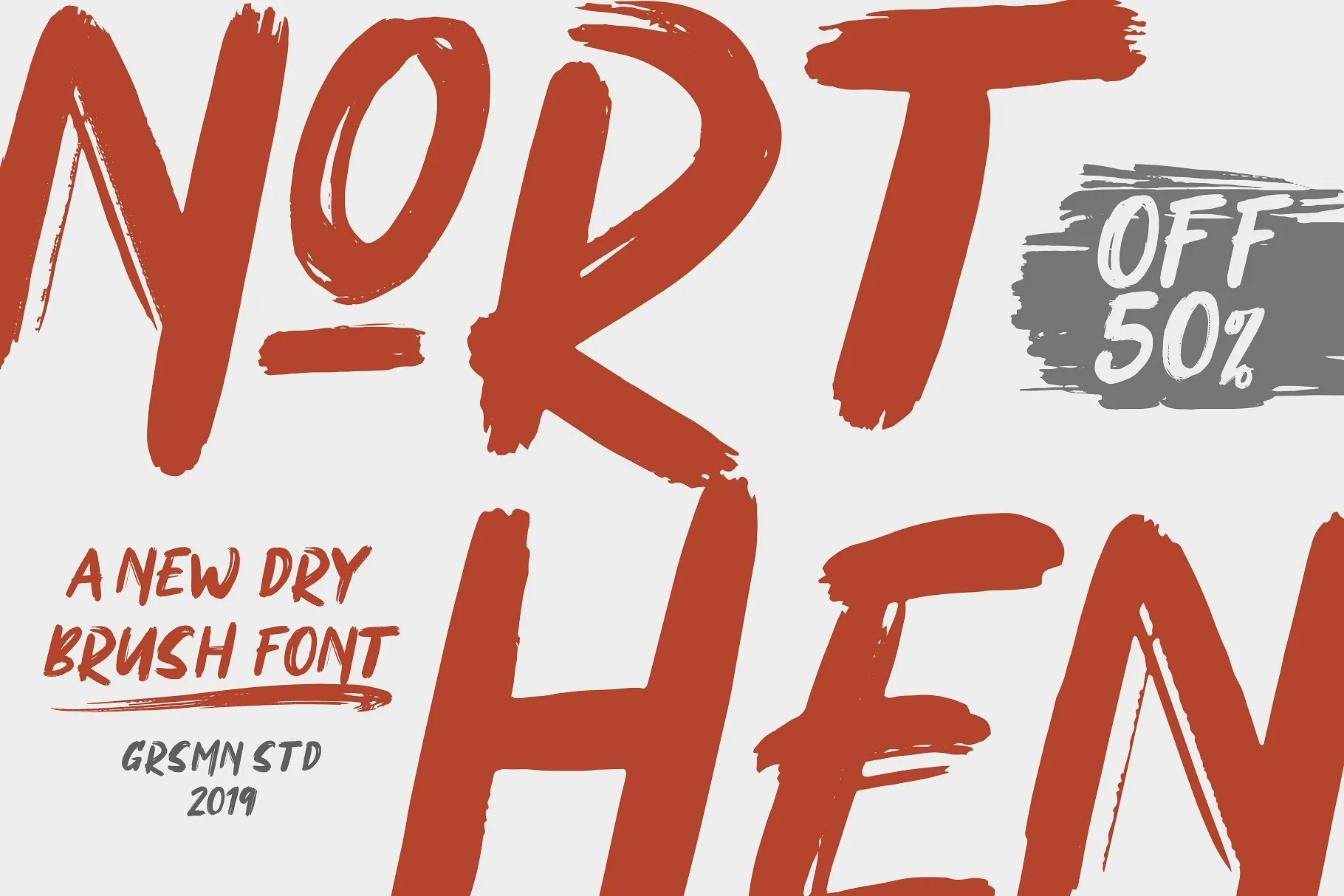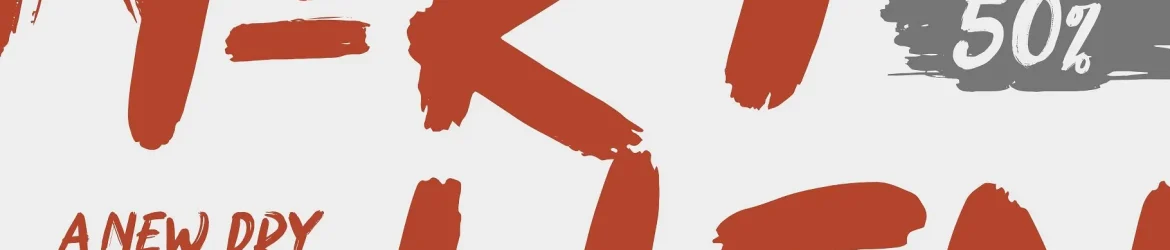
Northen Brush Font – Download Grátis
A fonte “Northen Brush Font” é uma nova opção para quem busca aperfeiçoar seus designs com um estilo moderno e elegante. Esta curiosa fonte script incorpora linhas arredondadas encantadoras com um toque urbano fresco, proporcionando um script refinado que certamente será capaz de dar destaque ao seu logo, imagens de marca, citações escritas a mão, embalagens de produtos, itens promocionais e postagens no redes sociais. Com o Northen Brush Font, seus trabalhos não só serão profundos em detalhes, mas também cheios de personalidade única e criatividade. Para designers que valorizam tanto uma atmosfera urbana moderna quanto um toque elegante, esta fonte é perfeita para suas necessidades. Não hesite em adicionar a sua colecção de fonts agora.